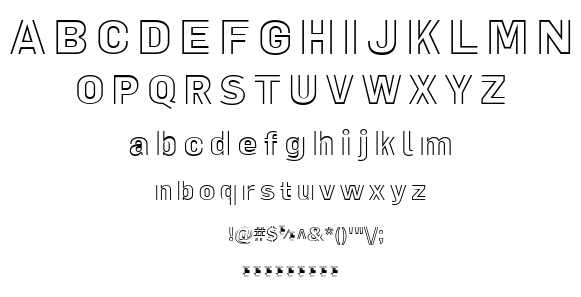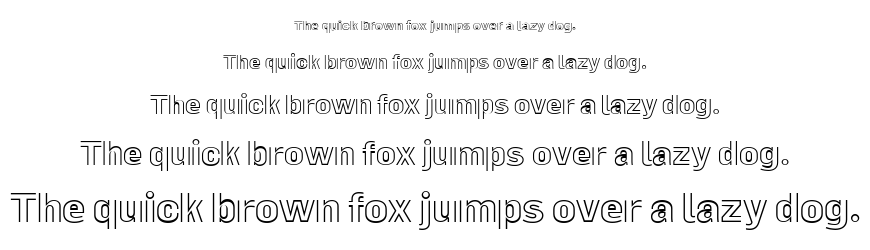
La Pejina font es mi primera tipografía continental, una sans serif de doble línea que homenajéa a Laredo en Cantabría y a toda la comarca pejina donde vivo y trabajo ahora. Cluster estrategico del Norte de España
The font is my first Pejina continental typography, a serif sans double line honors Laredo in Cantabria and the entire region pejina where I live and work now. Strategic Cluster of Northern Spain
• Regular & Italic